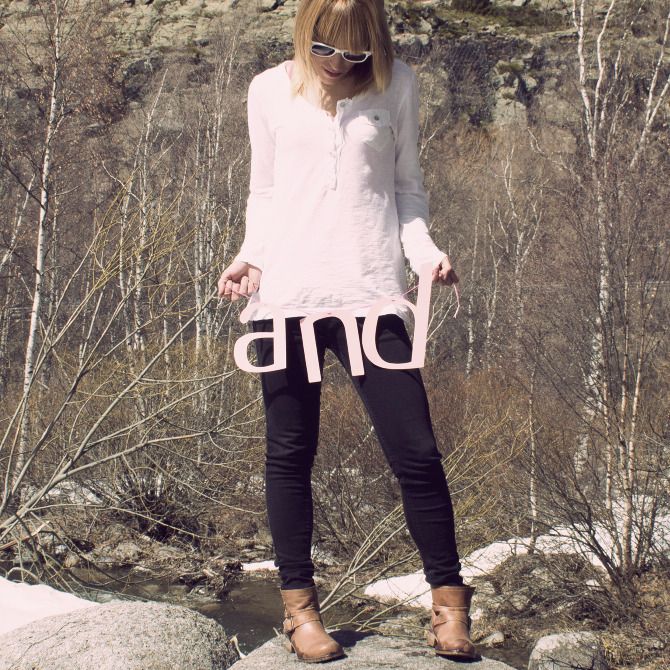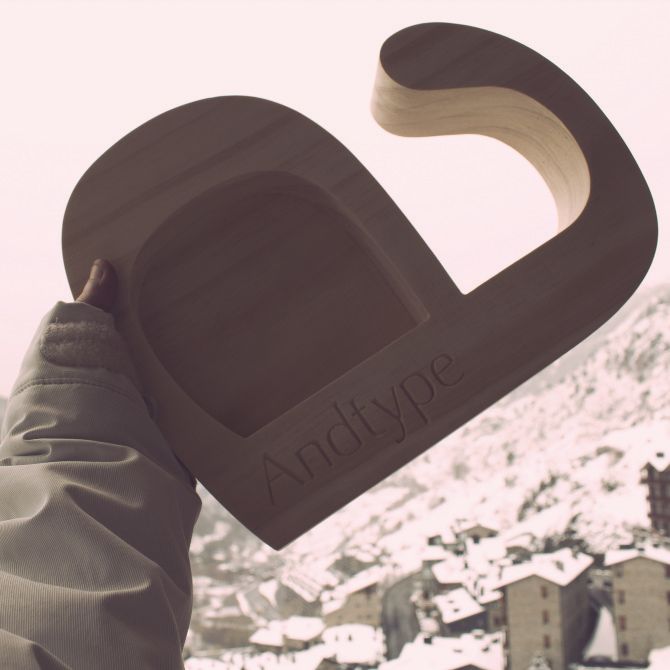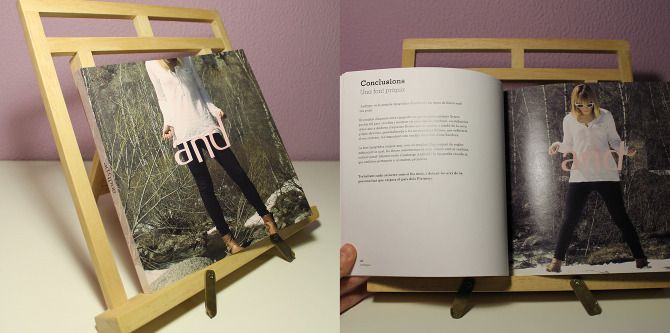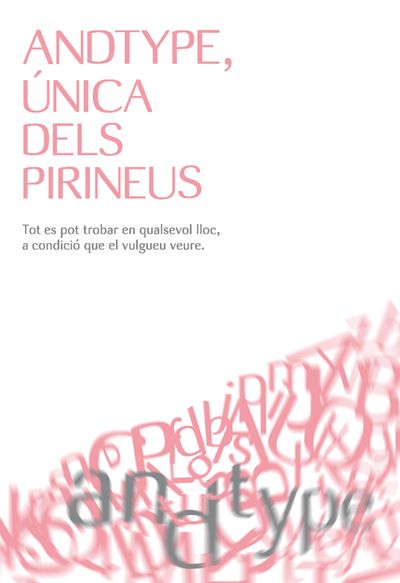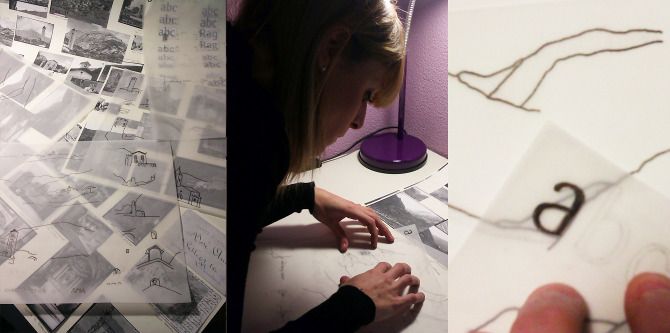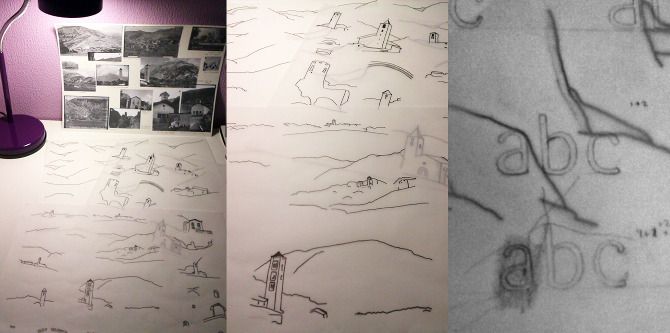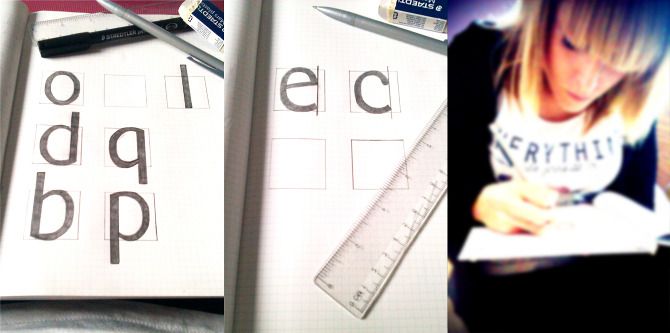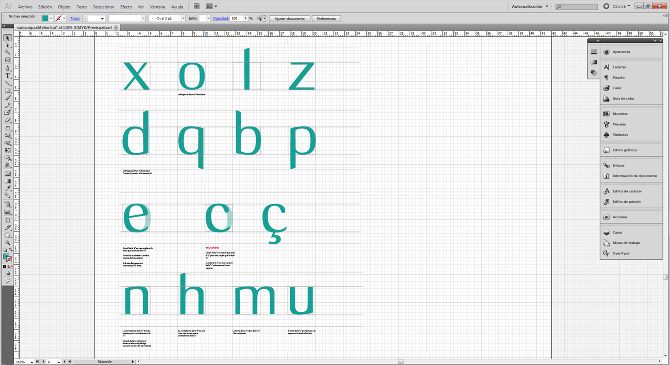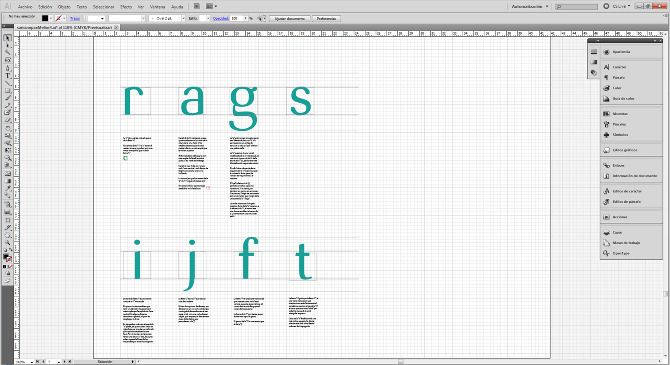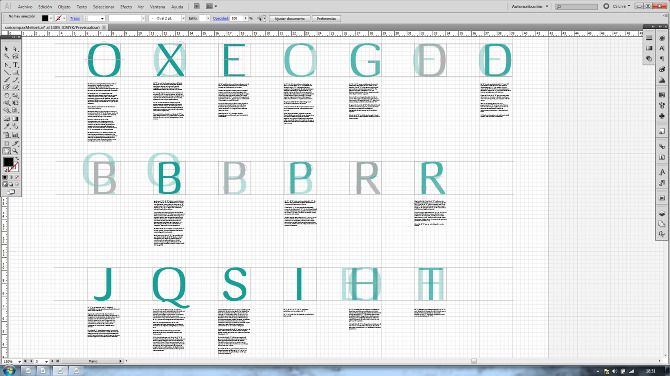
Tipografia Andtype
von Alexandra Echevarria Muñoz @ale_echevarria
Aquest projecte tipogràfic tracta de realitzar un anàlisi estructural del país Andorrà, i veure així la importància que pot atorgar a la tipografia, el seu exterior (històric, social, geogràfic...)
Combinant així línies i formes, intentant en la seva mesura que eren seleccionades del repertori que ens deixa el paisatge Andorrà, si escau, un autèntic inventari, i, combinades d’una forma peculiar, neix i es construeix, la nova expressiva tipografia.
La finalitat d’aquest projecte és veure que les fronteres del país comencen i acaben amb les formes que la tipografia -Andtype- ens deixa.